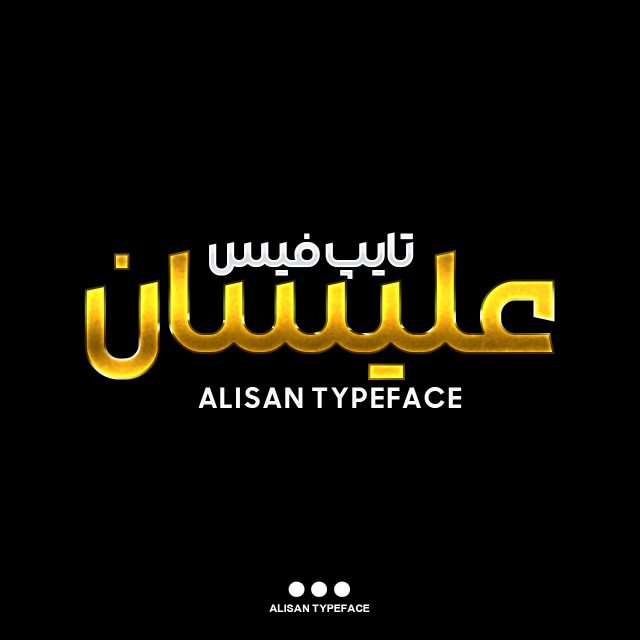
دانلود فونت فارسی علیسان Alisan Font
دانلود فونت فارسی علیسان Alisan یک گزینه خوب برای طراحی لوگو تایپ فارسی تایپ فیس علیسان اثر هاشم شهرزاد برای کلمات و عبارات کوتاه و بلند…
دانلود فونت فارسی علیسان
دانلود فونت فارسی علیسان Alisan
یک گزینه خوب برای طراحی لوگو تایپ فارسی
تایپ فیس علیسان اثر هاشم شهرزاد برای کلمات و عبارات کوتاه و بلند طراحی شده و بیشتر مناسب موضوعات تجاری و مدرن از قبیل کاور و اسلاید شبکه‌های اجتماعی و تبلیغات و بسته بندی می‌باشد. علیسان، ساختاری هندسی و منظم دارد. در حروف فونت علیسان، گِلیف ها با محیط دایره هم‌راستا شده‌ و با دقت و سخت‌گیری زیادی بر اساس شکل‌های مربع و دایره طراحی شده است.
تایپ فیس علیسان برای استفاده در اکثر آثار تبلیغاتی به ویژه برای استارتاپ‌ها و کسب و کارهای خلاق و نوین بسیار مناسب است. در این فونت از فونت مکمل انگلیسی نیز استفاده شده است تا در متن های فارسی، انگلیسی نیازی به تغییر فونت نداشته باشید.
پیشنمایش های تایپ شده با فونت فارسی علیسان